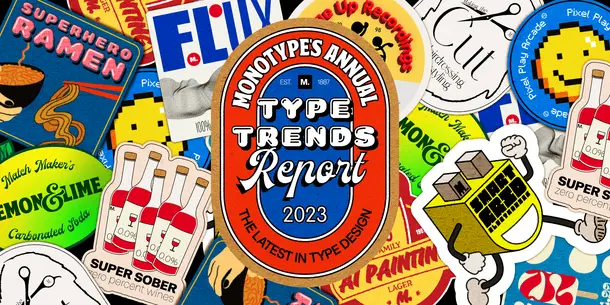
2023年タイプトレンドレポート:
革新と文化的インスピレーションの視点でデザインを考察
Monotype Type Trends 2023 report cover featuring typography and design trends.
変化し続ける世界を通して、技術・多様性・包摂性、そして文化の時代性からトレンドを捉え、クリエイティビティの未来を示す
【米国マサチューセッツ州ウーバン】フォントとフォントテクノロジーの分野で世界をリードするMonotypeは本日、「2023年タイプトレンドレポート:タイプデザインの最新状況」を発表いたしました。デザインを通して世の中の今を考える本レポートでは、Monotype Studioが特定した10のトレンドから、ブランドにとって表現とデジタルタッチポイントの重要性が増していることが明らかになりました。デザイン業界がさまざまなデジタルプラットフォームでタイポグラフィを使ってどのようにブランドと世界とをつなげているかを各トレンドの調査と分析をもとに概説しています。
「書体は技術や今日のトレンドをめぐる会話への入り口です。このレポートには有益でためになる作品がまとめられています。どれも魅力的で、刺激的です。そして何よりも、デザインという大海原に広がるうねりを捉えています。10のトレンドから、私たちの日々の暮らしが文字の形にどのような影響を与えているかが見えてきます」(Monotypeクリエイティブ・タイプディレクターTerrance Weinzierl)
文化、多様性、包摂性や、拡張現実(AR)、仮想現実(VR)といった主流になりつつある技術を背景に、本レポートではクリエイティビティに焦点を当て、技術によっていかにグラフィックデザインの領域が拡大しているかを紹介しています。以下は、本レポートで取り上げているトレンドの一例です。
● 昨年のトレンドの進化形である「Match maker」(組み合わせの妙)では、多様性、多彩さ、効果的な組み合わせを視覚的に表現しています。書体の多様さ、多彩さは、今の世代の考え方や価値観、目標、使命を常に映し出しています。人々の経験を表現するトレンドと言えます。
●「Smart grid」(スマートグリッド)はアートとサイエンスの融合で、四分円や半円でグリッド構造を巧みに崩しながら構築していきます。グリッドは主役でありながら、部分的に柔らかく処理され、さらに精密で洗練されたカットが施されています。
● コロナ禍を経て、遊び心のある世界が戻ってきました。縁取りや陰影を特徴とし、傾斜や歪み、曲線遠近法も多用する「Superhero」(スーパーヒーロー)が突如として目に飛び込んできます。世界中で人気のコミック映画が背景にあると思われるこのトレンドには、楽しく、遊び心のあるコミックのような雰囲気があります。
●「Super sober」(超シンプル)はさまざまなブランドやアプリ、通知が氾濫する中で、そのシンプルさを際立たせています。白と黒を基調とし、中央にシンプルに配置されることが多いデザインです。
● 世界が前進し続け、紙への依存度が低下し続ける中で、画面上では自由な動きが促進されています。「Flux」(可変性)というトレンドでは、シンボルや記号も含めたバリアブルフォントが画面の至る所で動き回っています。ARやVRに対応したデザインが、未知の3次元空間へとさらに突き進んでいきます。
「このレポートで紹介したトレンドの多くは、2022年に捉えたトレンドをさらに発展させ、そこから着想を得たものですが、同時にデザインの未来を示すものであり、いろいろな意味で私たちを取り巻く世界を解釈するためのガイドでもあります。私たちは毎年レポートを作成してきましたが、今回は世界のタイポグラフィの素晴らしさを称えるものとなりました。不毛な土地であっても、情熱と目的があればクリエイティビティは開花する、このことをレポートは伝えています」(Monotypeクリエイティブ・タイプディレクターEmilios Theofanous)